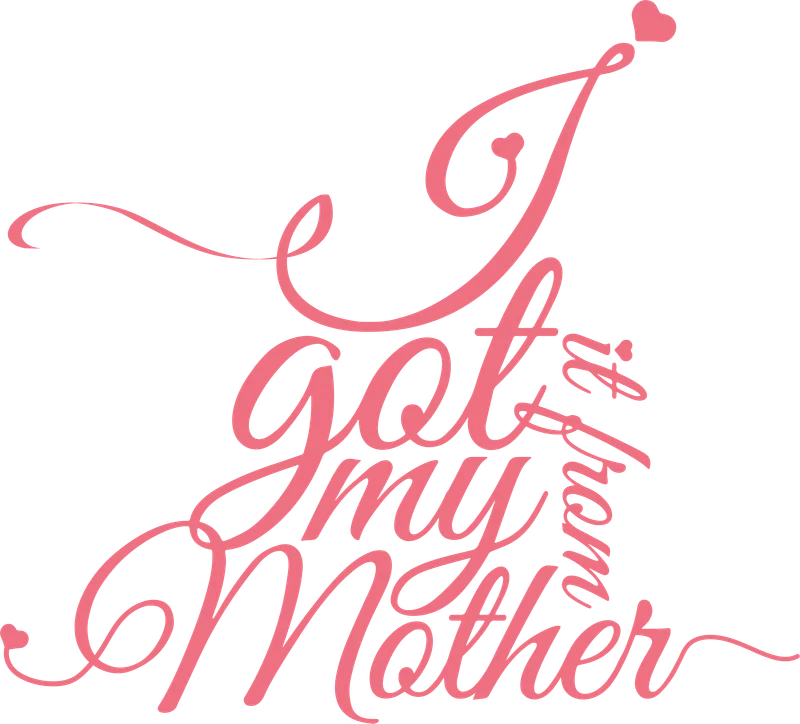
Tôi nhận được điều này từ mẹ - Font chữ tình cảm
Tôi nhận được điều này từ mẹ - Font chữ tình cảm — Thiết kế chữ 'I got it from my Mother' với font script mềm mại, thể hiện tình cảm với mẹ. Phù hợp in áo, quà tặng ý nghĩa. Có thể in chuyển nhiệt.
Trong hình có: chữ viết, trái tim
Phong cách: line-art · Cảm giác: yêu thương
Tông màu chủ đạo: hồng